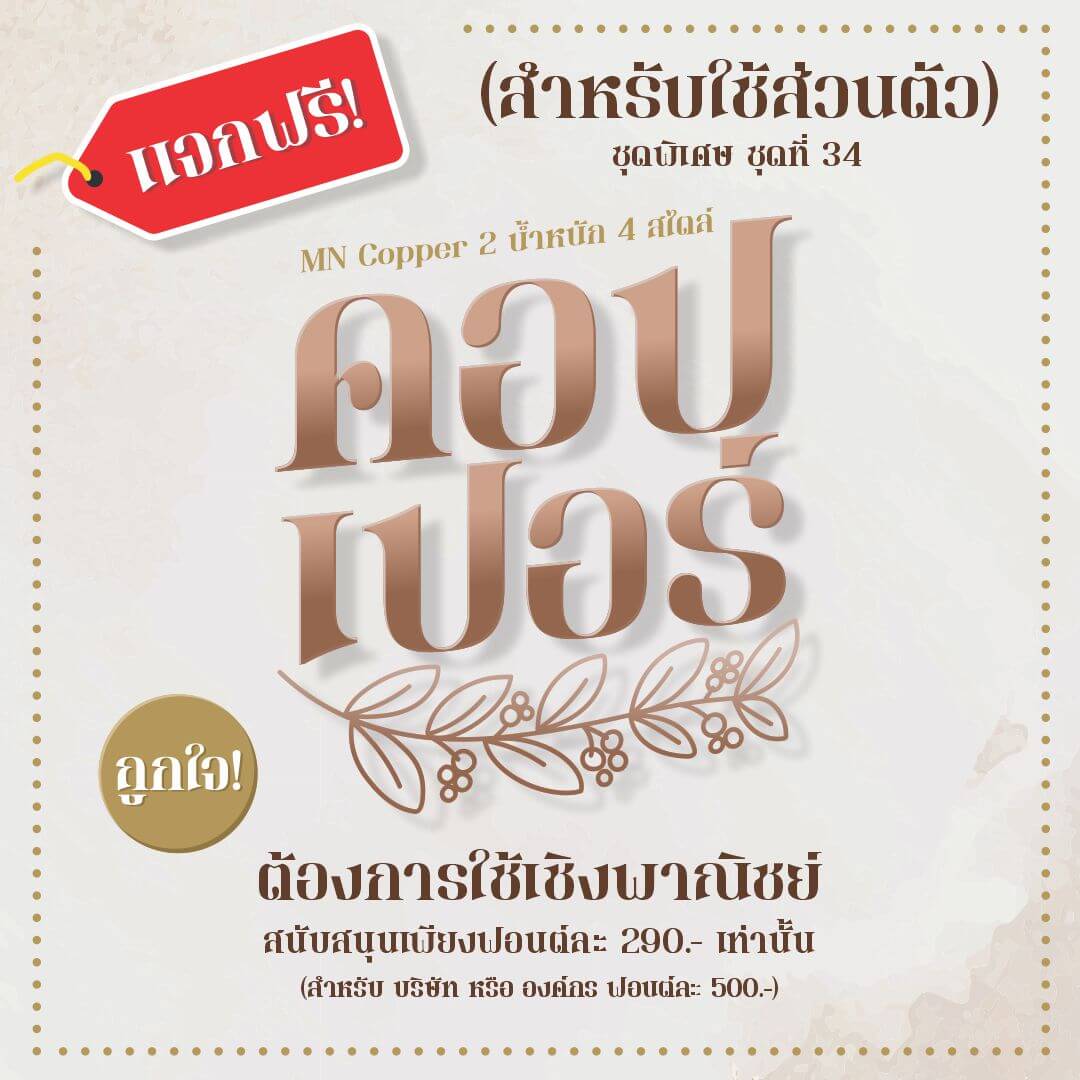
พบฟอนต์ไทยสวย ๆ สำหรับตกแต่งงานอาร์ตเวิร์ต ตกแต่งโน้ตให้สวยน่ารัก ๆ ทีมงานได้รวบรวมฟอนต์ไทยใหม่ ๆ จากเว็บไซต์ ฟอนต์.คอม มาแนะนำให้ดาวน์โหลดกันค่ะ
แนะนำ 9 ฟอนต์ไทย ตกแต่งงานกราฟิก งานป้าย งานโฆษณาสวย ๆ จาก ฟอนต์.com
ฟอนต์ที่นำมาแนะนำกันวันนี้จะเป็นไทยสวยน่ารัก สำหรับตกแต่งงานกราฟิก งานป้าย หรืองานโฆษณาต่าง ๆ หากสนใจนำไปใช้ด้านการศึกษา การทำงานส่วนตัวที่ไม่เกี่ยวข้องกับเชิงพาณิชย์ก็สามารถดาวน์โหลดฟรีกันได้เลย
1. Hioly (ไฮโอลี่)
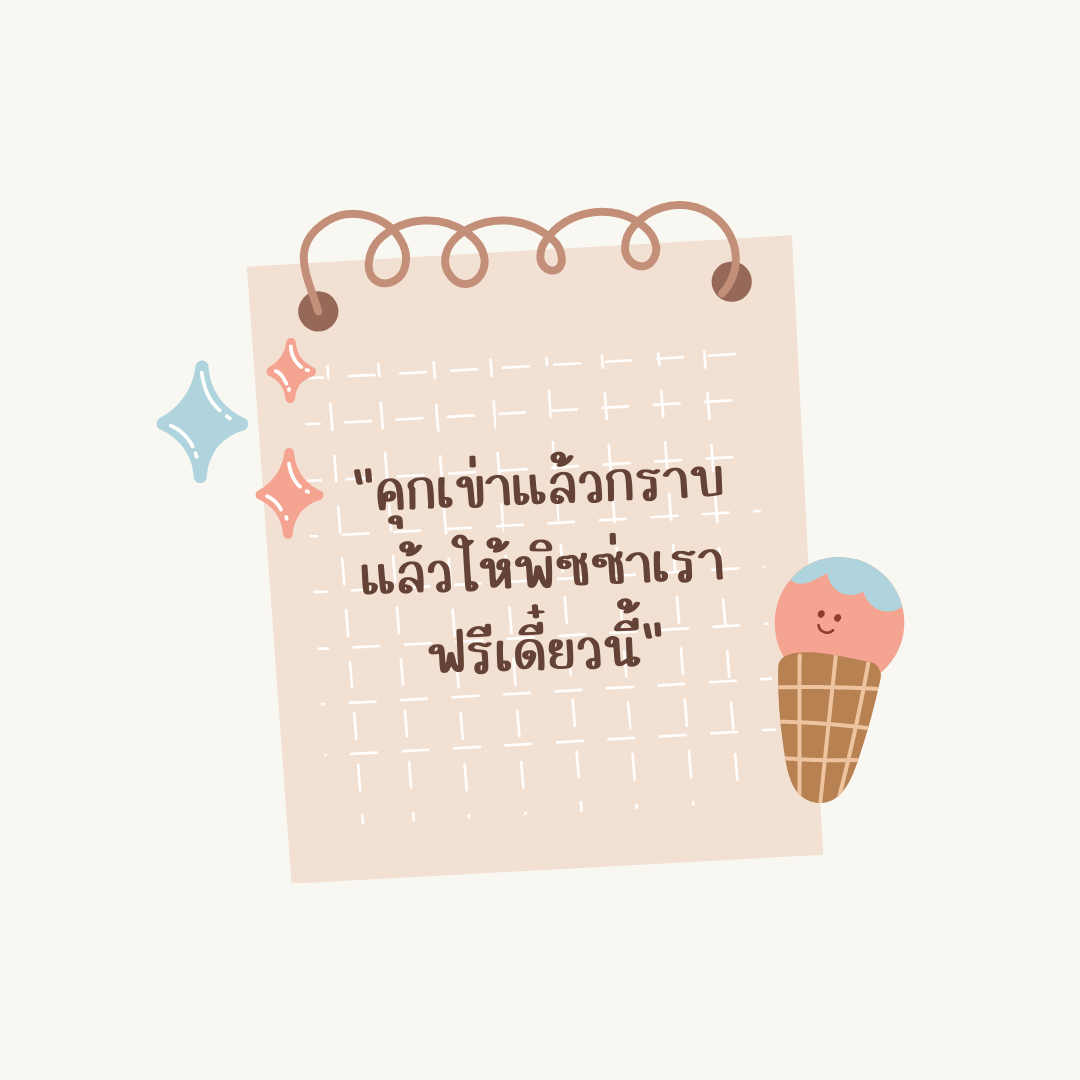
2. เอฟซี ออร์บิท (FC Orbit)
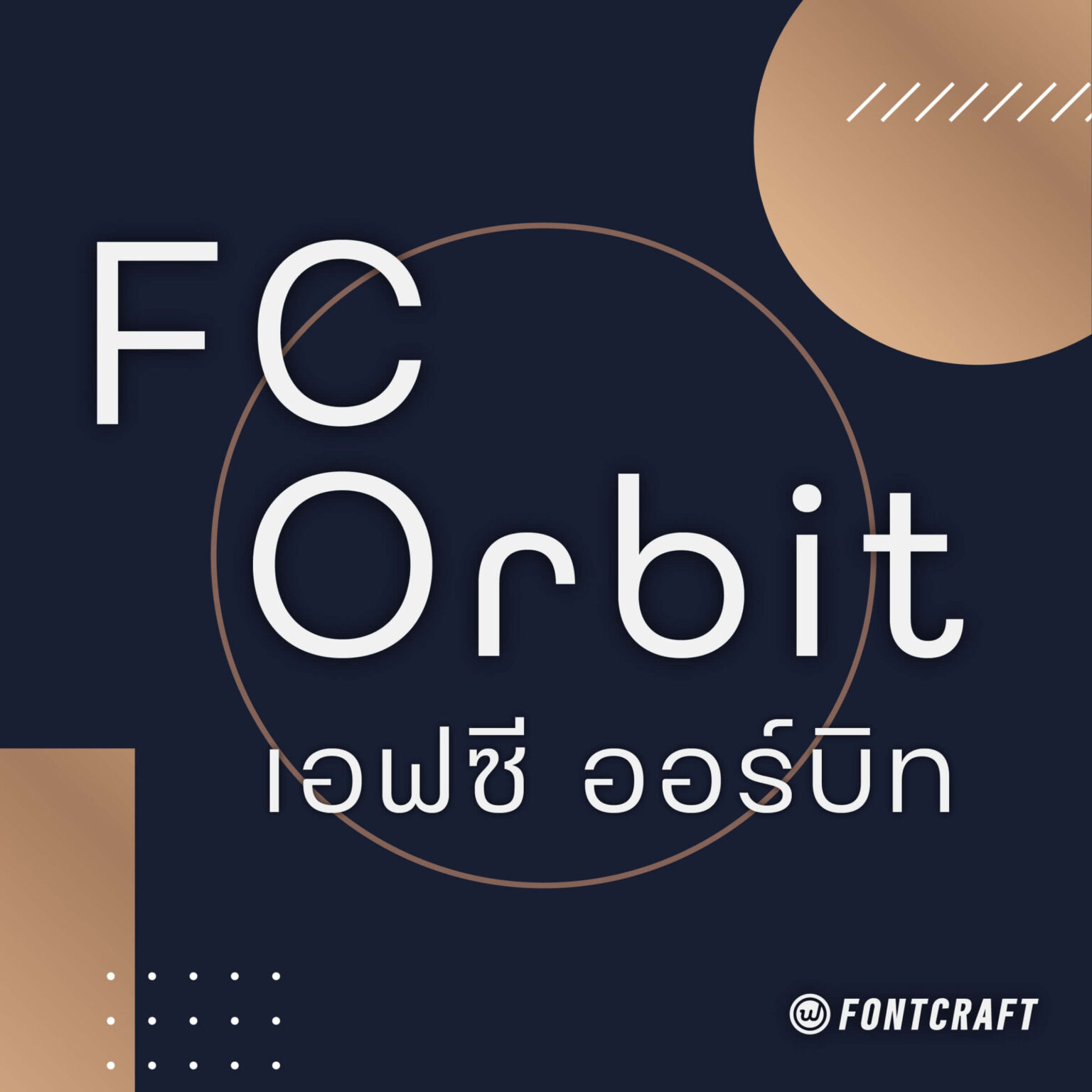
3. Bobby (บ๊อบบี้)
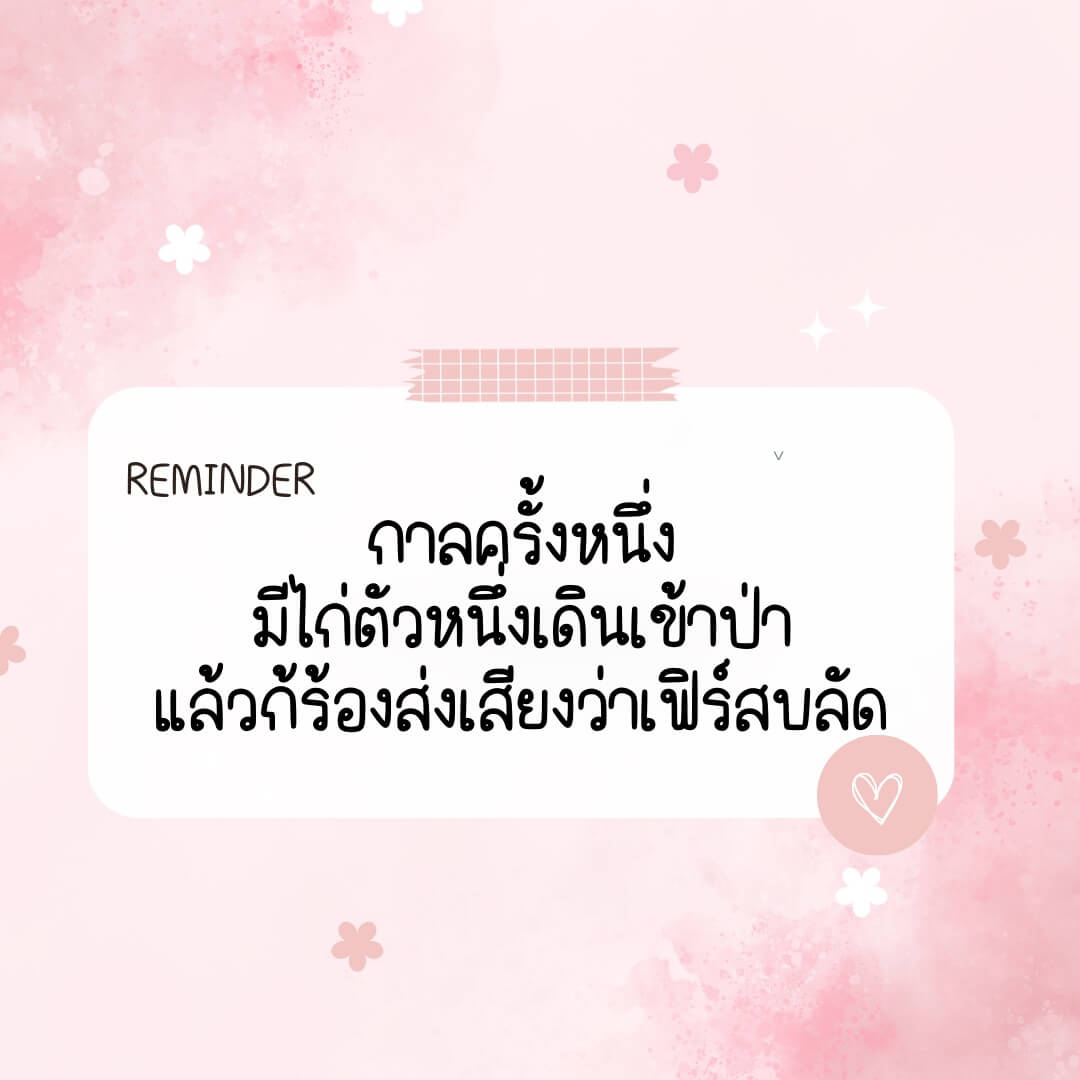
4. ซาลาเปา (MN Salapao)
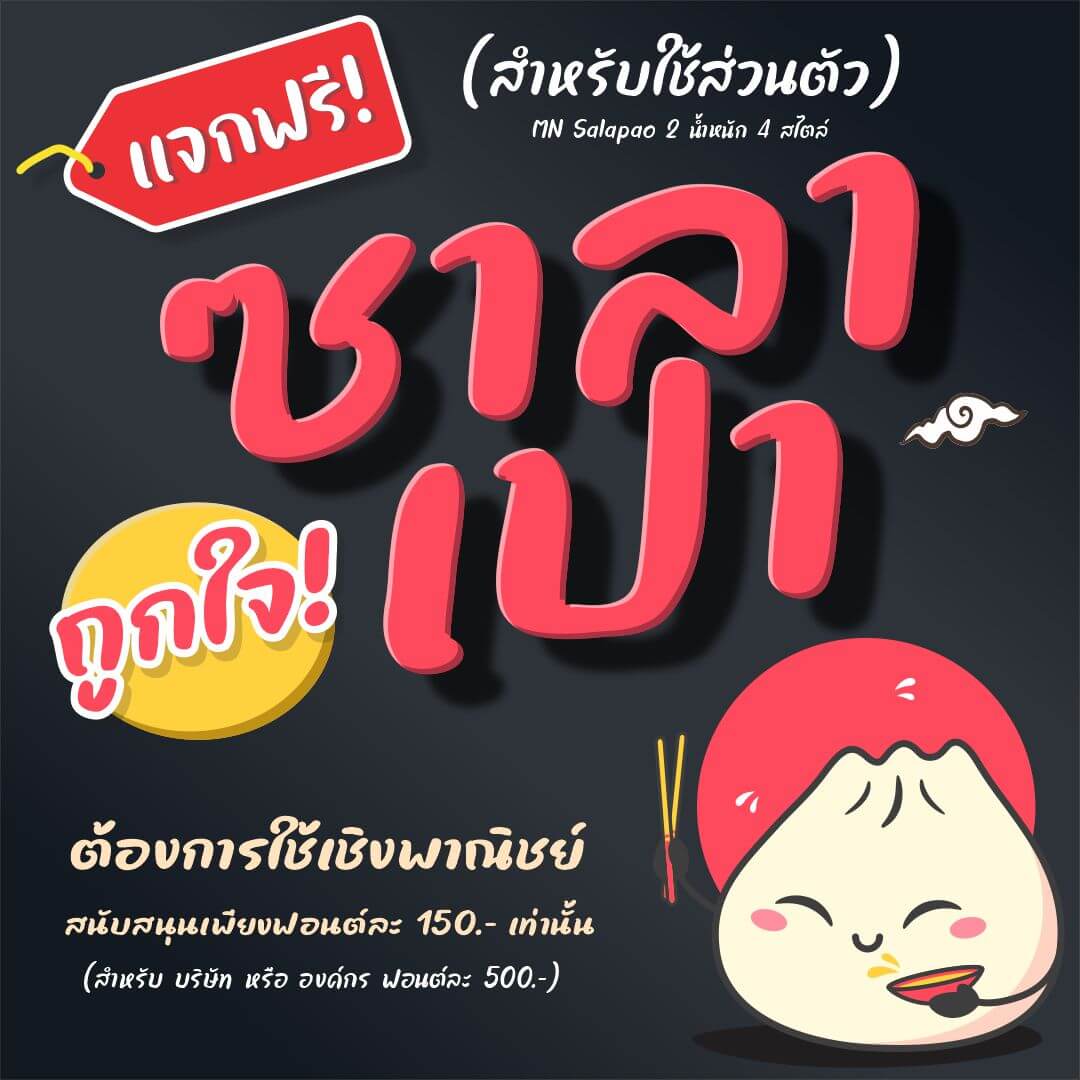
5. เอฟซี มัคคิอาโต้ (FC Macchiato)
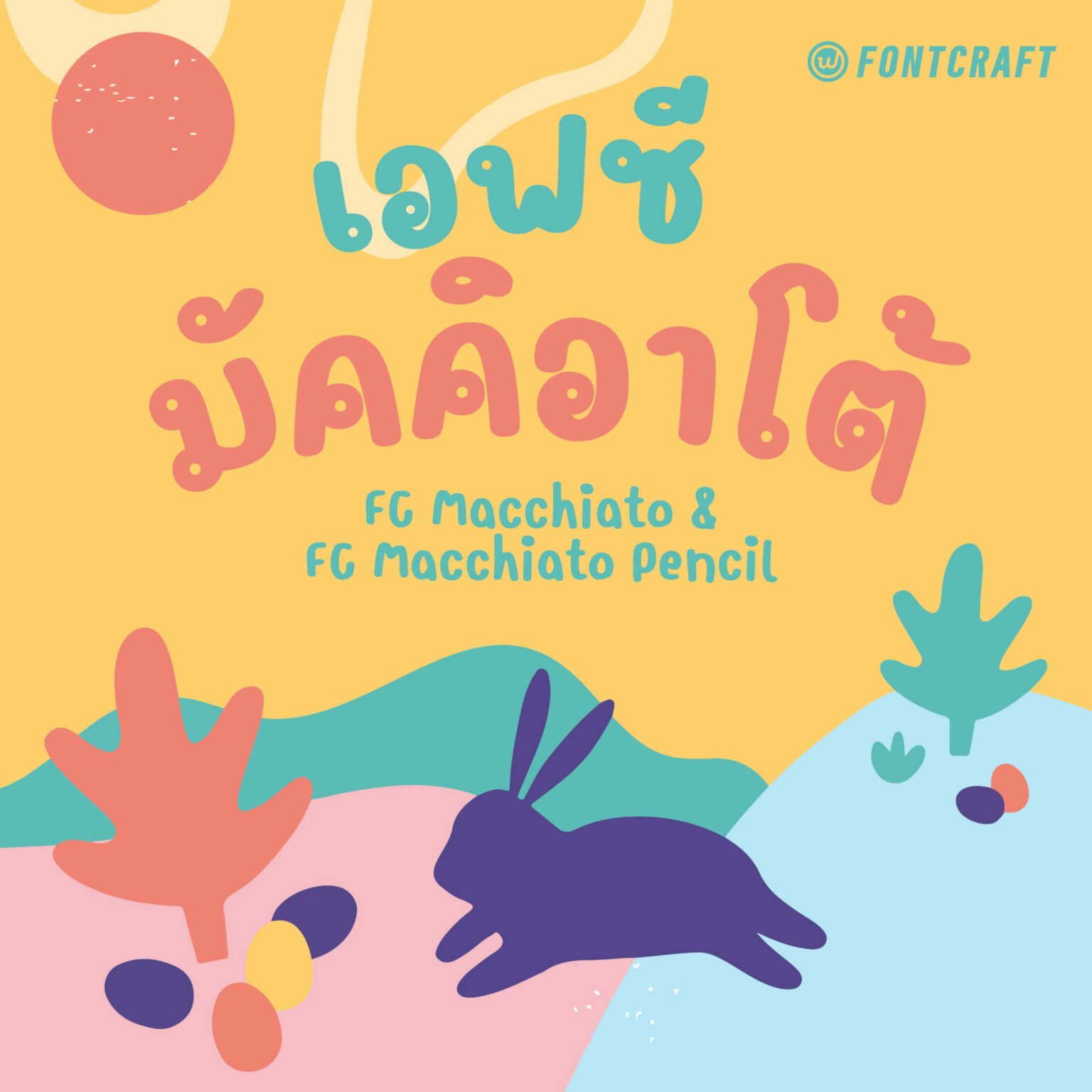
6. โน๊ต (Noted)
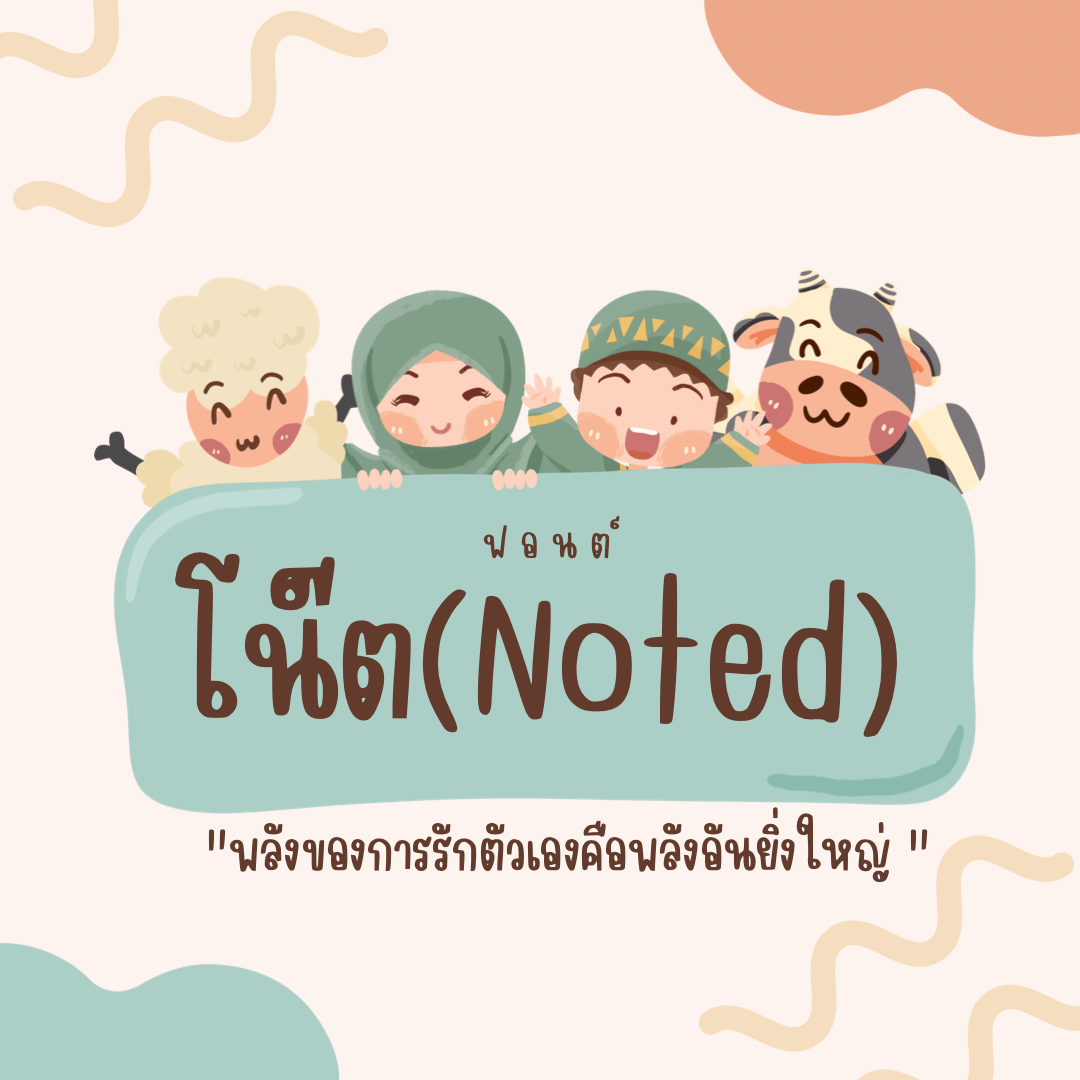
7. ขาหมู (MN Kha Mu)
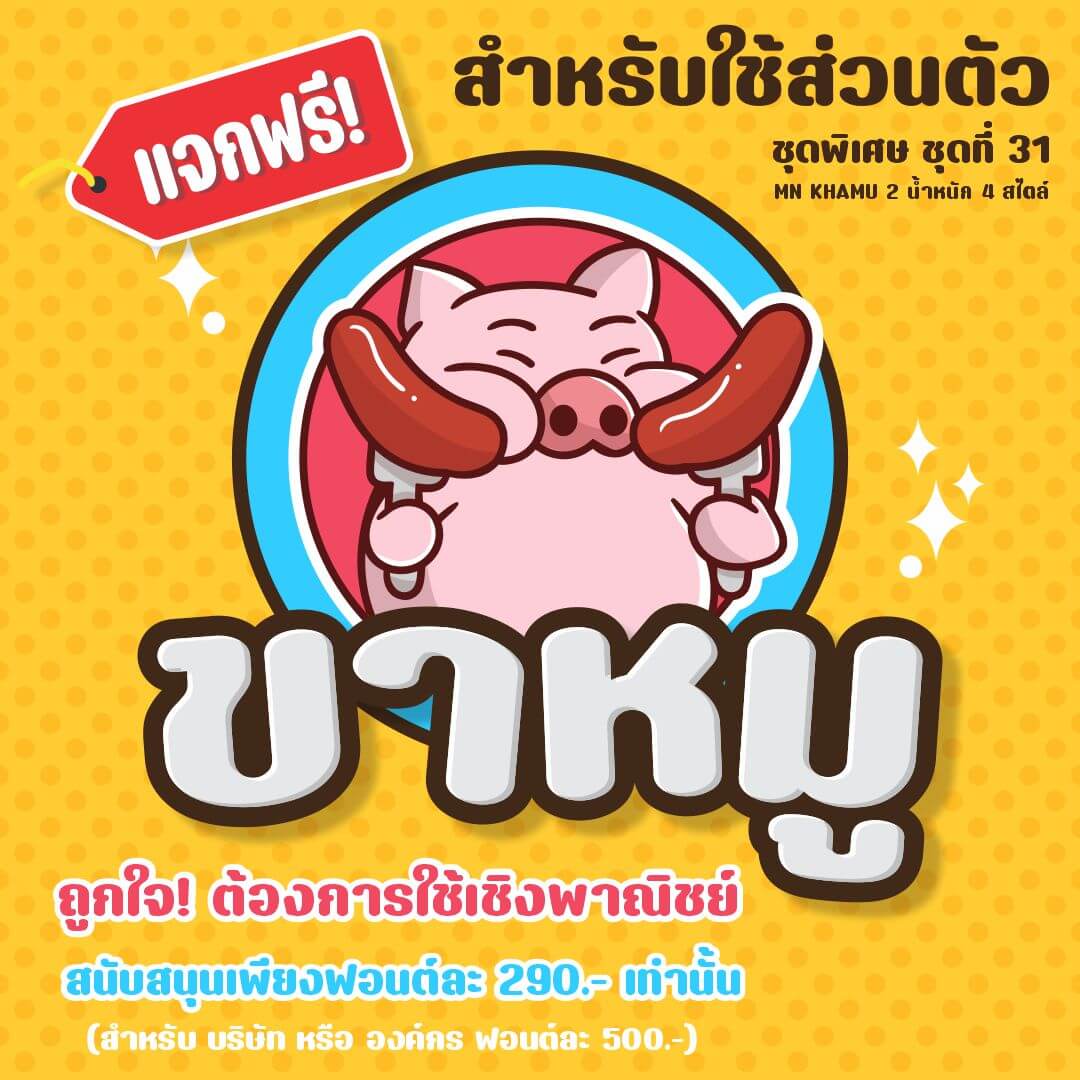
8. กุ้งเผา (MN Kung Phao)
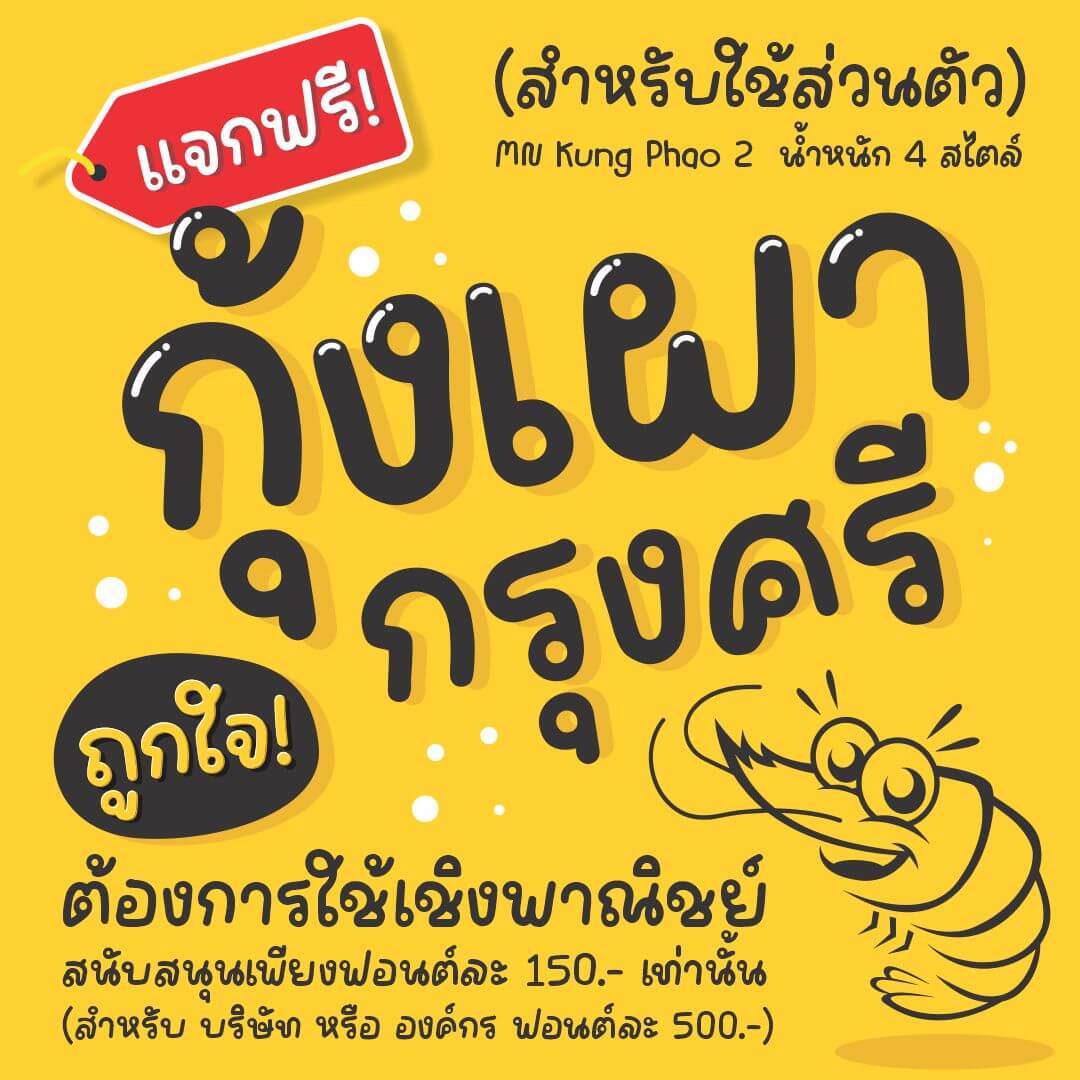
9. คอปเปอร์ (MN Copper)